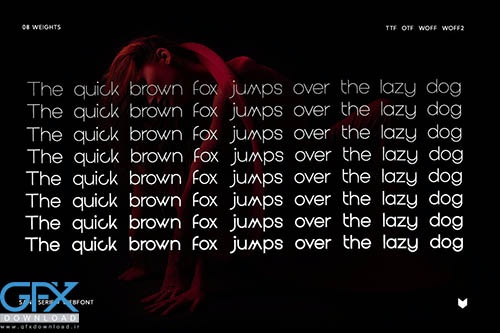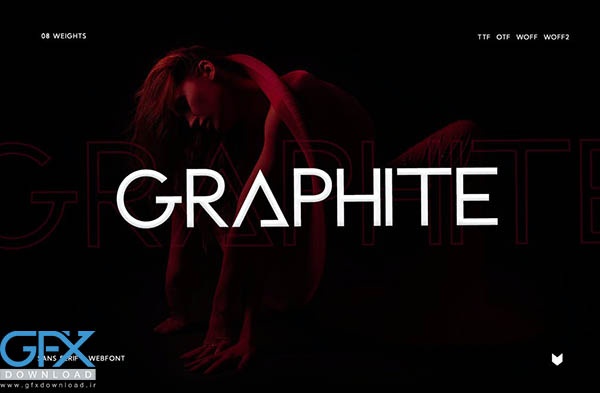
دانلود مجموعه فونت گرافیت Graphite Pro Typeface. یک فونت مینیمال با طراحی جذاب با مجموعه ای از کاراککتر های شیک ، ظریف و زیبا است. گرافیت یک تایپ فیس مدرن مینیمالیست با فونت های وب است. این یک فونت بسیار متنوع است که در اندازه های بزرگ و کوچک عالی کار می کند. گرافیت برای برندسازی، آرم ها، سرفصل ها، زیرنویس ها عالی است. یا به سادگی به عنوان یک پوشش متنی شیک برای هر تصویر پس زمینه. 8 وزن مختلف گنجانده شده است. TTF، OTF، WOFF، WOFF2 و WebFonts گنجانده شده است.